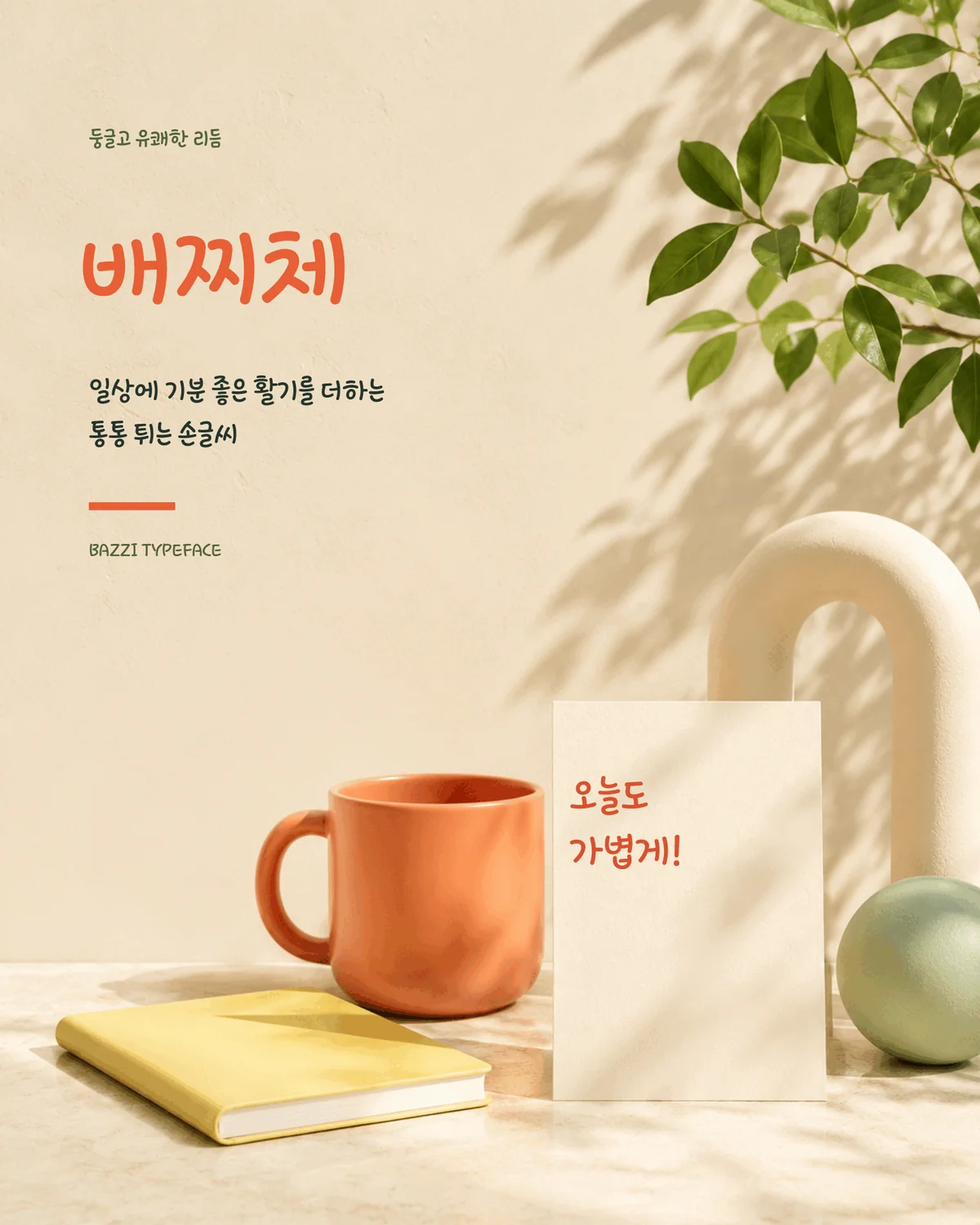
넥슨 배찌체 — 넥슨에서 배포하는 무료 폰트입니다. 둥글둥글한 자형과 자연스러운 필기감으로 배찌의 유쾌한 이미지를 담아낸 손글씨체
넥슨의 대표 캐릭터 배찌의 이름을 딴 서체입니다. 여기서 흔한 오해를 하나 짚고 가야 합니다. 캐릭터의 생김새를 글자로 옮긴 것이 아니라, 넥슨이 연 배찌 손글씨 공모전에서 최우수작으로 뽑힌 이용자의 필체를 바탕으로 만든 서체입니다. 배찌가 쓴 글씨라는 설정인 셈입니다.
손글씨가 원본인 만큼 형태가 불규칙하고 장난스럽습니다. 파일에서 재어 보면 획이 고르지 않고 글자마다 리듬이 달라, 기계로 그린 글자에서는 나오지 않는 인상을 냅니다.
굵기는 하나입니다. 말풍선이나 짧은 캐치프레이즈처럼 귀여운 톤이 필요한 자리에 맞고, 본문이나 격식 있는 문서에는 맞지 않습니다. 무료로 상업적으로 쓸 수 있지만 넥슨 서체 공통으로 임의 수정과 편집이 금지되어 배포된 형태 그대로 써야 합니다.